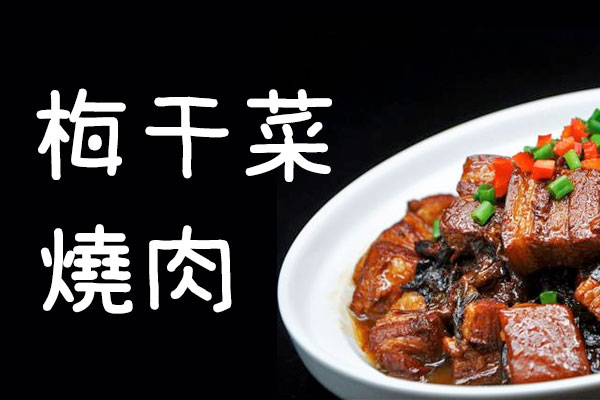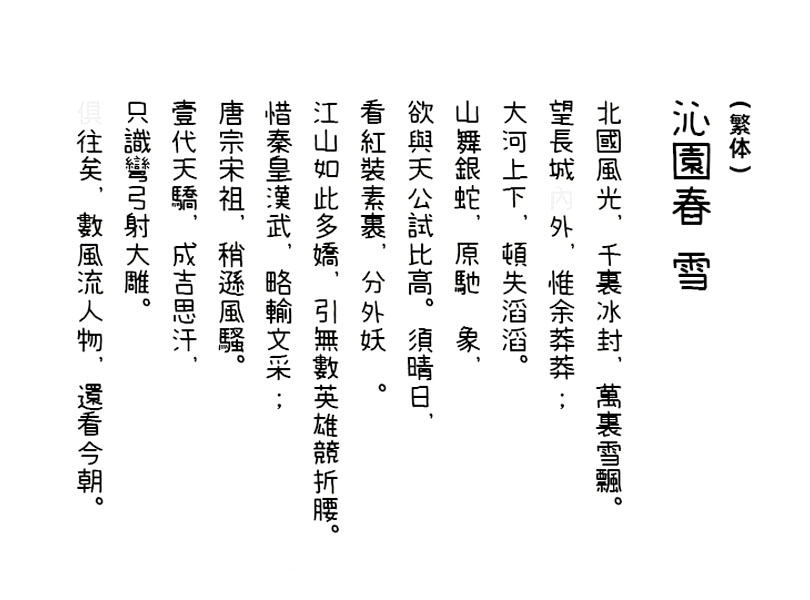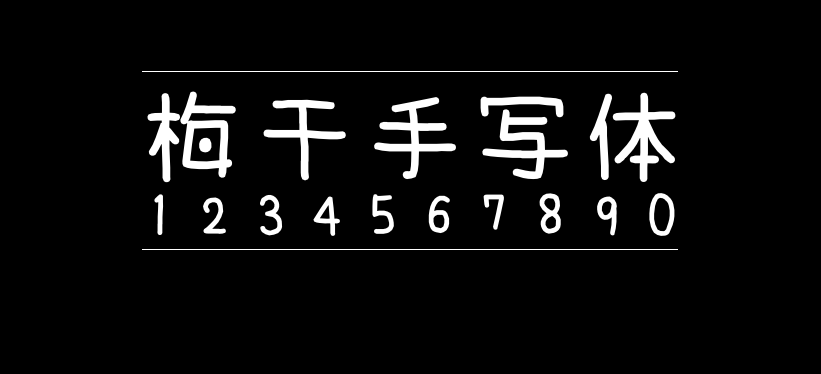
梅干手写体
梅干手写体(梅干フォント、umeboshi font)是日本设计师toga先生创建的手写字体,精心书写的圆字非常容易阅读,非常适合休闲、娱乐方向的设计。
梅干手写体收录了平假名、英文数字、半角·半角英文数字、符号、JIS第一、第二水准、IBM扩展汉字。 简体字数存在不全的情况,但是繁体还是比较齐全。